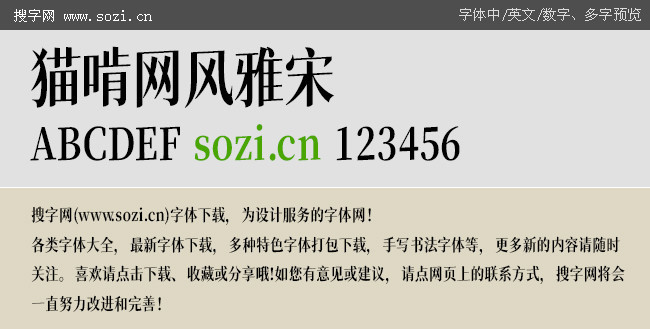
貓啃網(wǎng)風(fēng)雅宋
搜字網(wǎng)提供一款貓啃網(wǎng)風(fēng)雅宋中文藝術(shù)字體下載,貓啃網(wǎng)風(fēng)雅宋字體是基于獅尾四季春改造獲得的,通過(guò)程序壓縮字體寬度,并把字體向上拔高,只有一個(gè)字重,采用獅尾四季春SC-Bold,字體支持免費(fèi)自由商用。